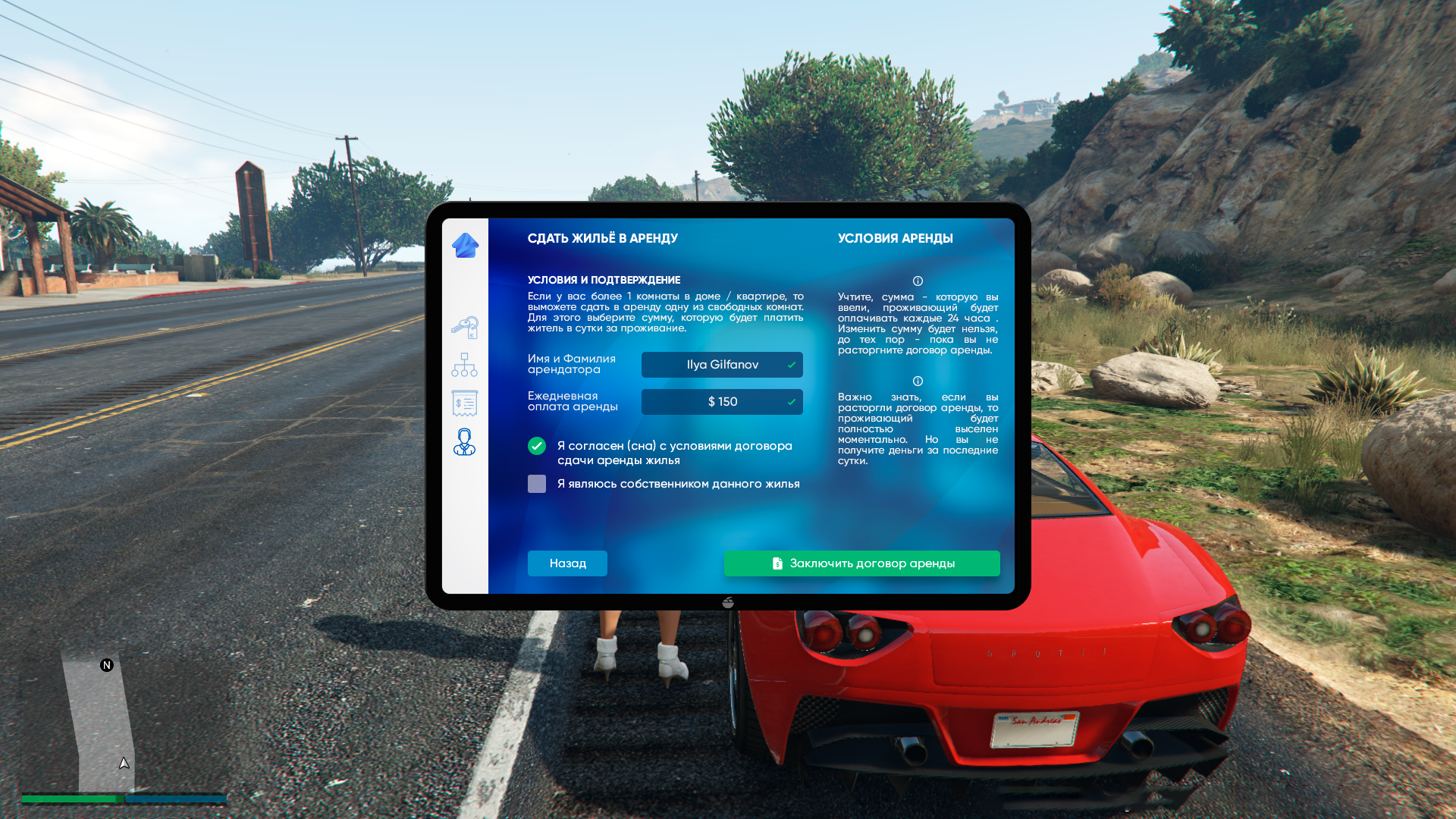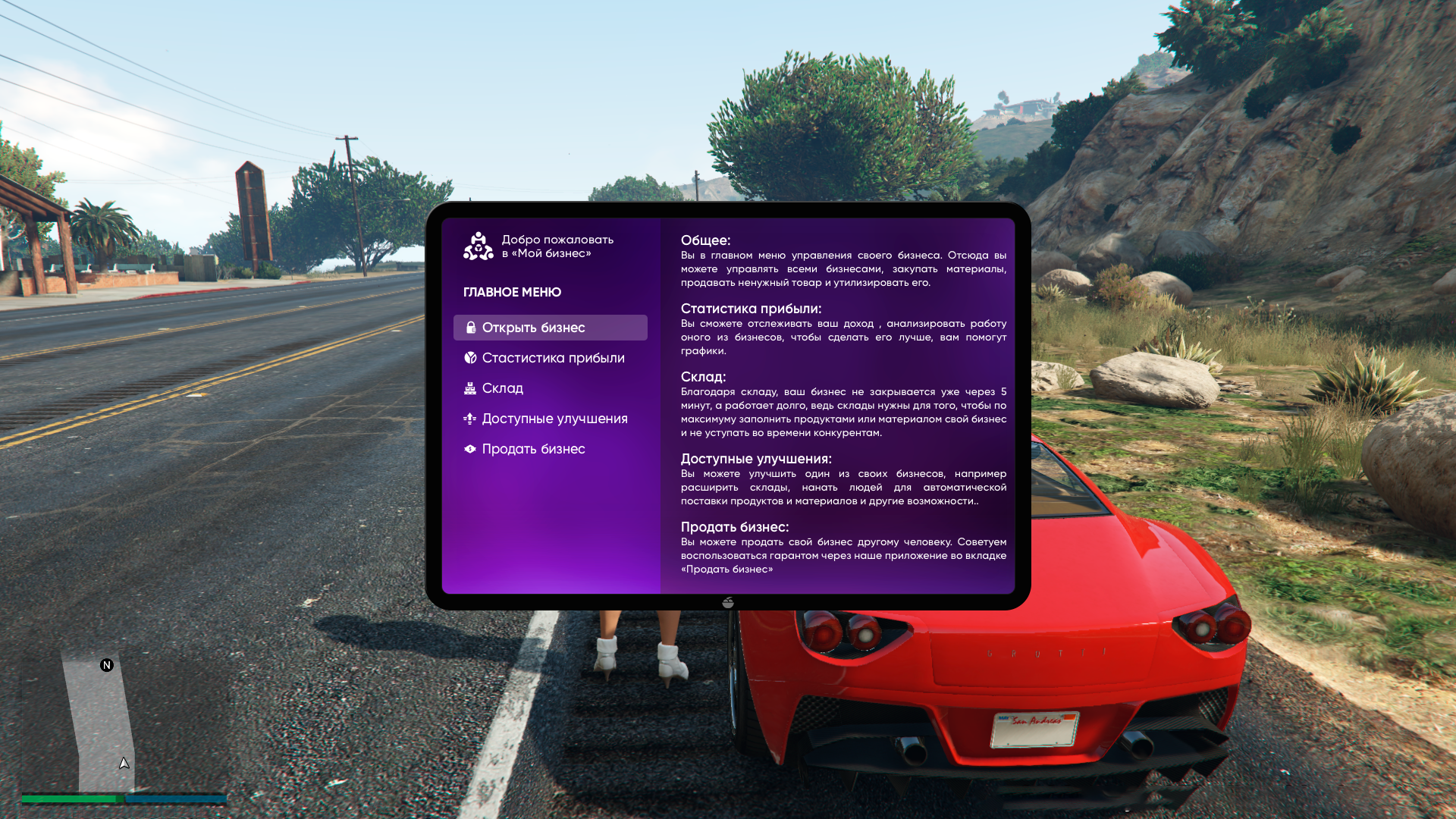
Шрифт
Привет коллеги, у меня такой вопрос..
Все мы знаем Windows 10, и многие наверное сталкивались с тем, что шрифты рендерятся просто убого, они не такие как на MacOS, а на маке работать не всегда хочется, железо там слабже у меня, да и экран меньше, а тут у меня RTX 2080 Ti и монитор взял новый, процессор и оперативки 64, не хвастаюсь, а просто говорю почему хотелось бы на Win 10 работать чаще.. Но вот просто сгораю от того, что в том же фотошопе в 13 ,14,15 px шрифт просто убогий, ну реально убогий, даже если выбираю другие значения в редактировании текста, там есть выбор рендера, от Windows, ЖКД Windows , четкий, резки и т д.
Я рассчитываю на то, что тут есть ветераны в дизайне, люди, которые прошли через это, есть какие то варианты сделать рендер, пусть и не как на MacOS, но хотя бы лучше, чтобы он не был цветной при скейле...
P.S. Если увеличить мою картинку даже на чуток, вы сразу увидите о чем я. Более того и так видно, что шрифт просто убогий в плане рендера. На Маке он очень хороший!
MacOS
WINDOWS 10